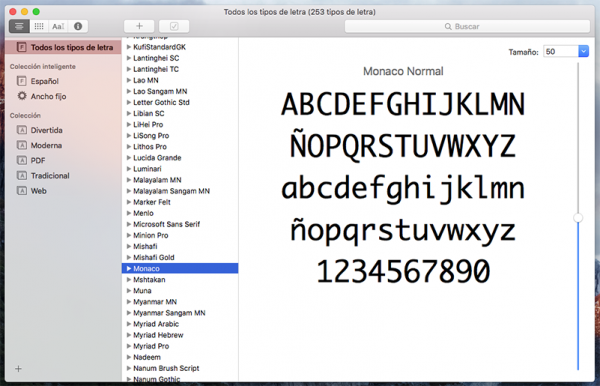
Steve Jobs y la tipografía digital. © Norman Seeff / Rolling Stone
Steve Jobs y la tipografía digital
Macintosh, Steve Jobs y la tipografía digital
Si la tipografía digital nació con Macintosh, Steve Jobs fue definitivamente su padre. Y fue él mismo quien se encargó de reconocerlo y difundir la historia detrás de su creación, en aquel famoso discurso que brindara en la Universidad de Stanford en 2005. El cofundador de Apple recordaba entonces la anécdota que se vinculaba a una de las decisiones más difíciles que tuvo que tomar en su juventud: abandonar por motivos económicos los estudios en el Reed College. Y si el joven Jobs se vio en la necesidad de dejar sus estudios, no abandonó en cambio el deseo de seguir aprendiendo, y supo buscarse el modo de asistir como oyente a las clases que realmente consideraba provechosas: “En aquella época la Universidad de Reed ofrecía la que quizá fuese la mejor formación en caligrafía del país. En todas partes del campus, todos los pósters, todas las etiquetas de todos los cajones, estaban bellamente caligrafiadas a mano. Como ya no estaba matriculado y no tenía clases obligatorias, decidí atender al curso de caligrafía para aprender cómo se hacía. Aprendí cosas sobre el serif y tipografías sans serif, sobre los espacios variables entre letras, sobre qué hace realmente grande a una gran tipografía. Era muy bello, histórica y artísticamente, de una forma que la ciencia no puede capturar, y lo encontré fascinante”, recordaba el CEO de Apple frente a los estudiantes de Stanford.
Steve Jobs. Steve Jobs y la tipografía digital
Robert Palladino, profesor de caligrafía y monje trapense
De aquel modo, en 1972, aparecía en la vida del joven Jobs, el personaje que encendería su pasión por la tipografía, el profesor de caligrafía y monje trapense, Robert Palladino. En sus clases se formaron muchos artistas, tipógrafos y diseñadores gráficos. Y si bien Jobs no pertenecía a ninguna de estas ramas y nada de lo que allí se aprendía parecía tener alguna aplicación práctica en su vida, diez años más tarde, aquella experiencia comenzaría a cobrar sentido: “Diseñamos el Mac con eso en su esencia. Fue el primer ordenador con tipografías bellas. Si nunca me hubiera dejado atraer por aquél curso concreto en la universidad, el Mac jamás habría tenido múltiples tipografías, ni caracteres con espaciado proporcional. Y como Windows no hizo más que copiar el Mac, es probable que ningún ordenador personal los tuviera ahora. Si nunca hubiera decidido dejarlo todo, no habría entrado en esa clase de caligrafía y los ordenadores personales no tendrían la maravillosa tipografía que poseen”, se enorgullecía Steve Jobs.
Robert Palladino. Steve Jobs y la tipografía digital
Susan Kare, la madre de la tipografía digital
Así, el cofundador de Apple atribuía a la influencia de Palladino la razón de ser de las elegantes fuentes del Mac; pero había algo que Jobs se olvidaba de mencionar, la influencia de otro personaje fundamental en la historia de esta creación. Porque si Steve Jobs fue el padre, Susan Kare tuvo necesariamente que ser la madre de la tipografía digital.
Cuando finalmente en 1983 hubo que demostrar al mundo que Macintosh era un ordenador pensado para las artes gráficas, la compañía fichó a la joven Kare, una recién graduada en Bellas Artes de la Universidad de Nueva York, para que diseñase los iconos del nuevo sistema operativo y las primeras fuentes no monoespaciadas para ordenadores. Así, nacieron Chicago, Geneva, Monaco y muchas otras fuentes, con y sin remate, formales y desenfadadas, que permitieron exhibir las potencialidades del Mac, para abrirse paso en un mercado todavía inexplorado. Si bien Kare se hizo más famosa por el diseño de iconos, fue también pionera en la creación de las más atractivas y originales tipografías digitales y tuvo una influencia definitiva en el desarrollo del diseño del lenguaje informático actual.
10 años de gestación y un final feliz
Desde aquella fascinación inicial de Jobs por el arte de Palladino, hasta el toque mágico de Kare que finalmente les diera nombres propios, más de 10 años debieron pasar para que las tipografías digitales pudieran cobrar vida. Una gestación que fue tan delicada y sutil como un fino trazo de tinta.
Catalogo tipográfico Mac. Steve Jobs y la tipografía digital